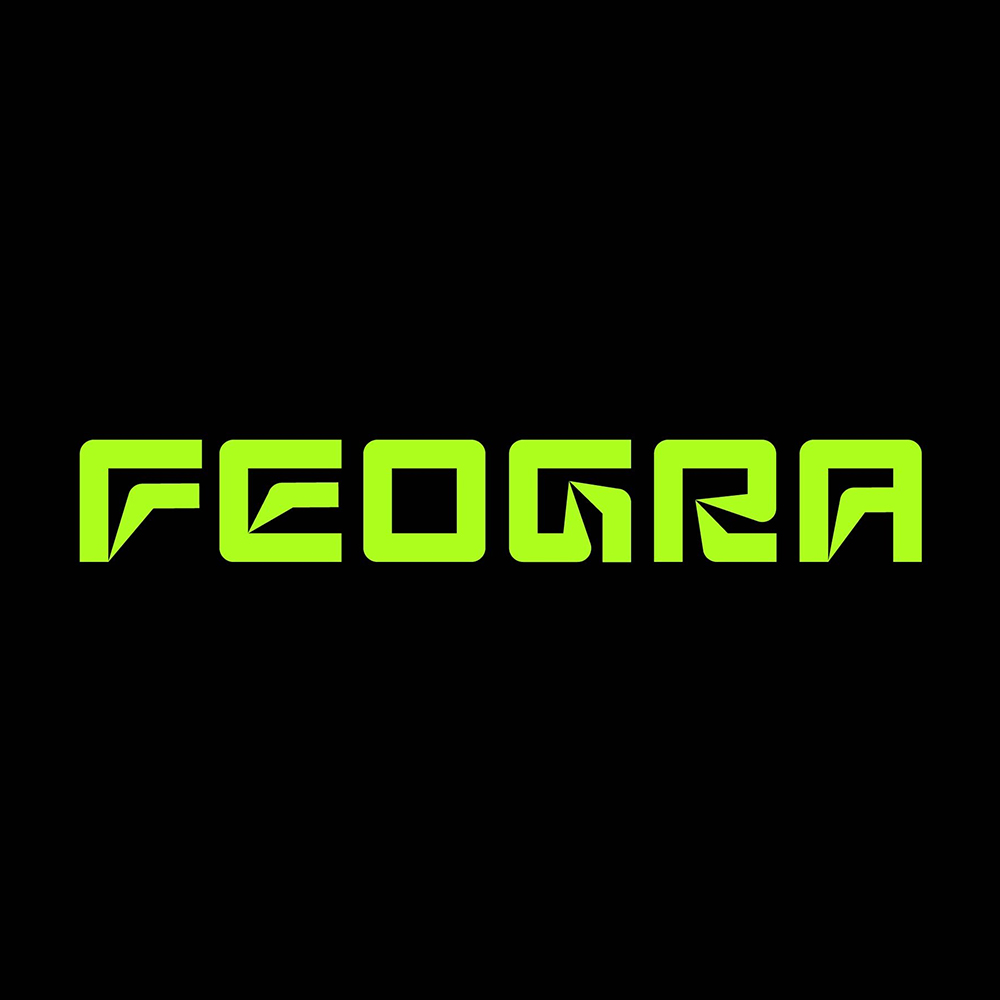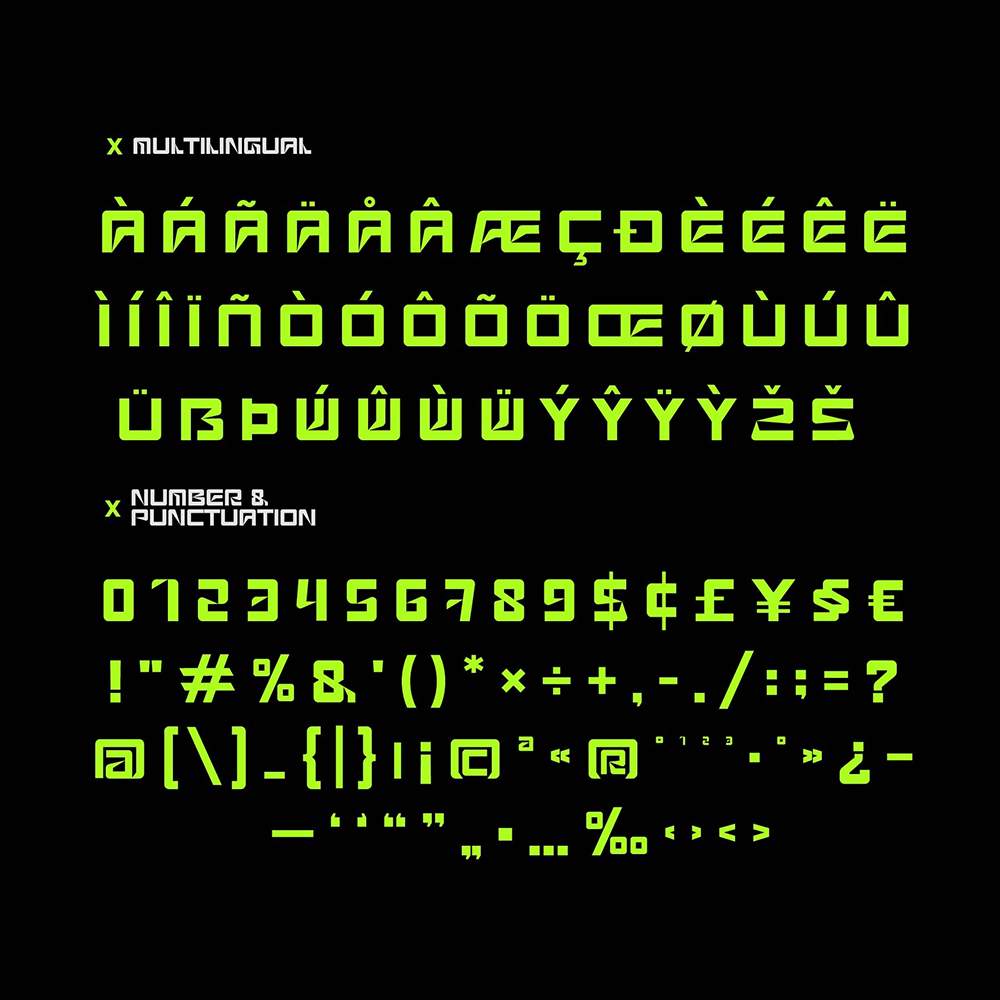
فونت پرمیوم و انگلیسیFeogra Font فونتی است که با الهام از شکل هندسی یک ربات و به سبکی مدرن طراحی شده است و ظاهری آیندهنگر و…
فونت پرمیوم و انگلیسیFeogra Font فونتی است که با الهام از شکل هندسی یک ربات و به سبکی مدرن طراحی شده است و ظاهری آیندهنگر و منحصر به فرد به این فونت میدهد، برای طراحی مدرن شما مناسب است و به یک فونت برجسته و پررنگ نیاز دارد. این فونت همچنین میتواند در پوسترها، مجلات و غیره اعمال شود. فئوگرا با حروف بزرگ، اعداد، نمادها و چندزبانه ارائه میشود. این فونت همچنین میتواند در پوسترها، مجلات و غیره اعمال شود. فئوگرا با حروف بزرگ، اعداد، نمادها و چندزبانه ارائه میشود.
مزایای استفاده از فونت لاتین Feogra چیست؟